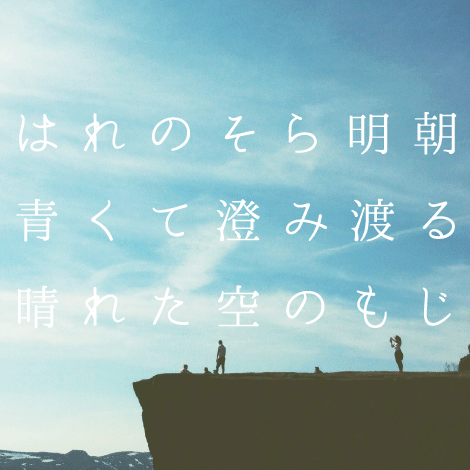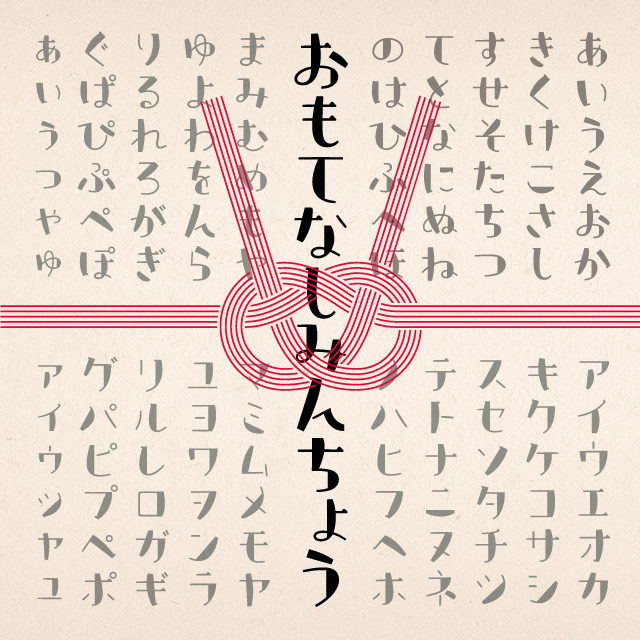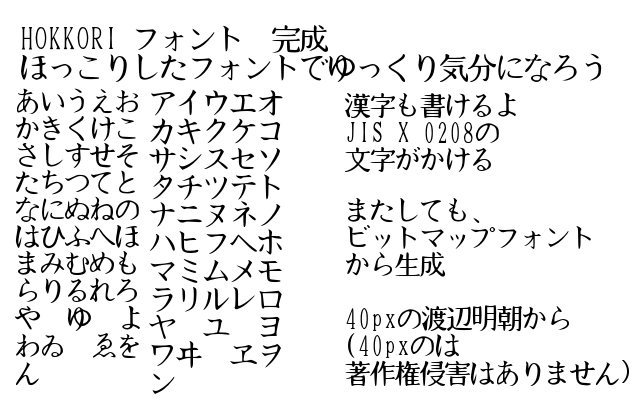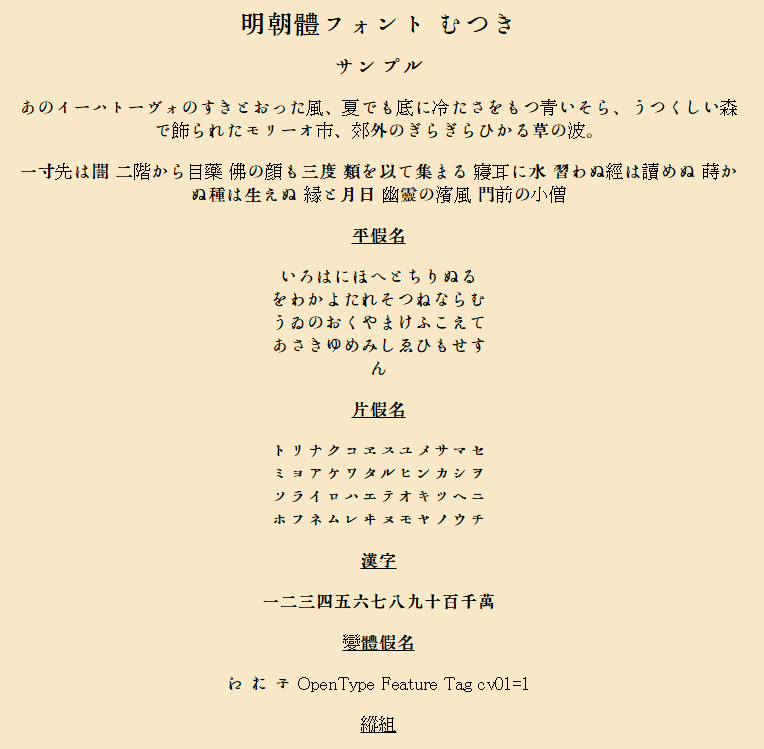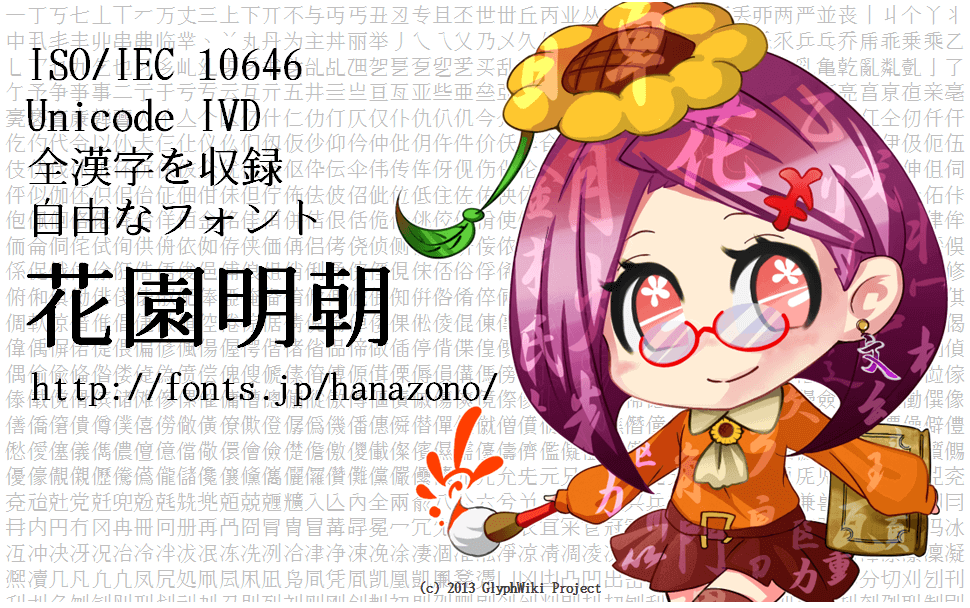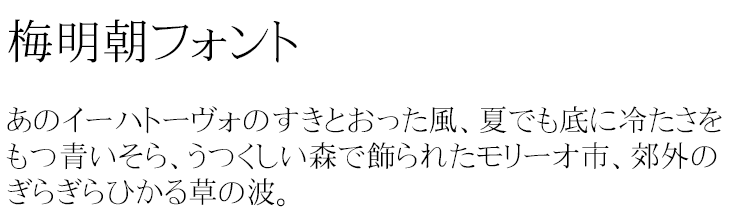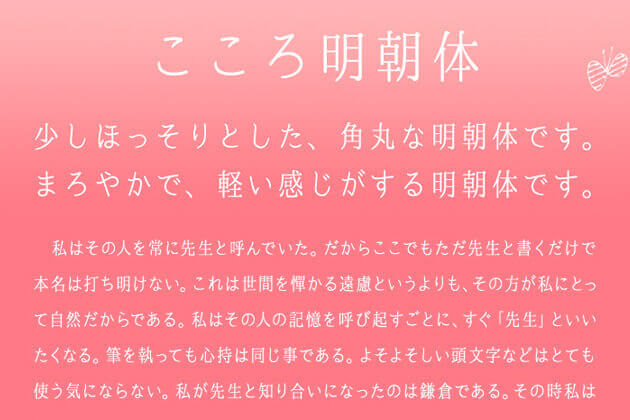
おすすめ明朝体フリーフォント27選
フォントの中でも明朝体は読みやすく多くのデザインに使われています。今回は、おすすめの明朝体フォントを27選まとめました。同じ明朝体でもイメージが異なるフォントもありますのでご自身の使用するデザインに合わせてご活用ください。
GL-アンチック
アンチック体かな文字フォント。ひらがな・カタカナ・記号等のみ。
HOKKORIフォント
よく見ると、しっかりした明朝ではない、しかし、明朝より安心感を与えてくれるほっこりするフォント。
IPA P明朝
“JIS X 0213:2004”をサポートし、商用・非商用に限らず無償で利用できる高品位な日本語フォントの明朝体パック。
IPAex明朝
和文文字(仮名や漢字など)は固定幅、欧文文字は文字幅に合わせた変動幅を基本とした実装を行われ、日本語文書作成の利便性の向上を目指したフォント。明朝体版。
IPA明朝
“JIS X 0213:2004”をサポートし、商用・非商用に限らず無償で利用できる高品位な日本語フォントの明朝体。
qoocRoman KT
アルファベットのセリフ体をベースにデザインした1byteカタカナフォント。ロマンチックさと神秘性を兼ね備えつつ、文字のカーブを緩やかにすることで、上品さが演出できます。
あおぞら明朝
7ウェイト展開のIPA明朝ベースの明朝体フォント。
いにしえよりつづくもの
明朝体のようでありながら筆で書いたような味わいと柔らかさのあるフォント
うつくし明朝体オールド
柔らかさ・レトロな味わい・漢字とかなのバランスなど求められるオールドスタイル明朝体のエッセンスは残しつつ、横へのつながりを感じさせるモダンなデザインになっているフォント。無料ダウンロードでき商用可能な漢字も入った日本語書体です。
おもてなし丸明朝
おもてなし明朝フォントの角を丸くしたデザインのフォント。より和風レトロな可愛さをイメージできます。商用利用の場合は製品版の購入が必要です。
おもてなし明朝
和風レトロなかわいさとモダンデザインの要素をもったフォント。
こころ明朝体
少しほっそりとした、角丸な明朝体。
ぬばたまおためしばん
新聞明朝ふうの見出し向け仮名書体。ひらがなのみを収録したお試し版。
はれのそら明朝
角丸ですっきりとした明朝体です。少しの墨だまりと、オールド系明朝体のエッセンスを含んだ日本語フォント。
はんなり明朝
やさしくて、ふんわりとした、ひらがなとカタカナをデザインしたフォント。
フォルみん
骨格は明朝的で肉付けはゴシック的なフォント。